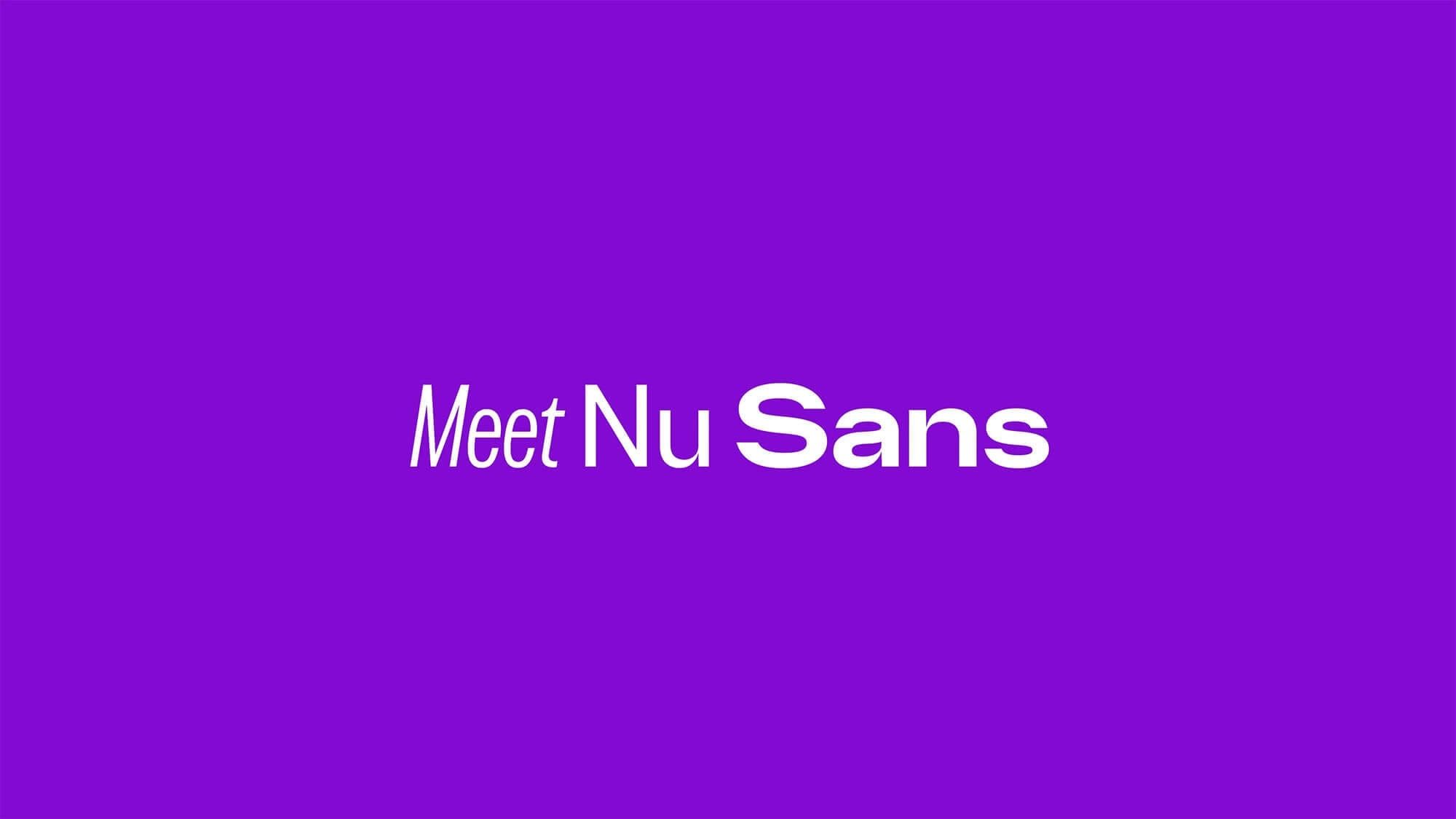
Nubank lança Nu Sans, sua primeira tipografia proprietária com 32 variações
Família tipográfica criada com a Blackletra Type Foundry nasceu do logo da marca e foi desenhada para funcionar como camada de segurança contra fraudes visuais